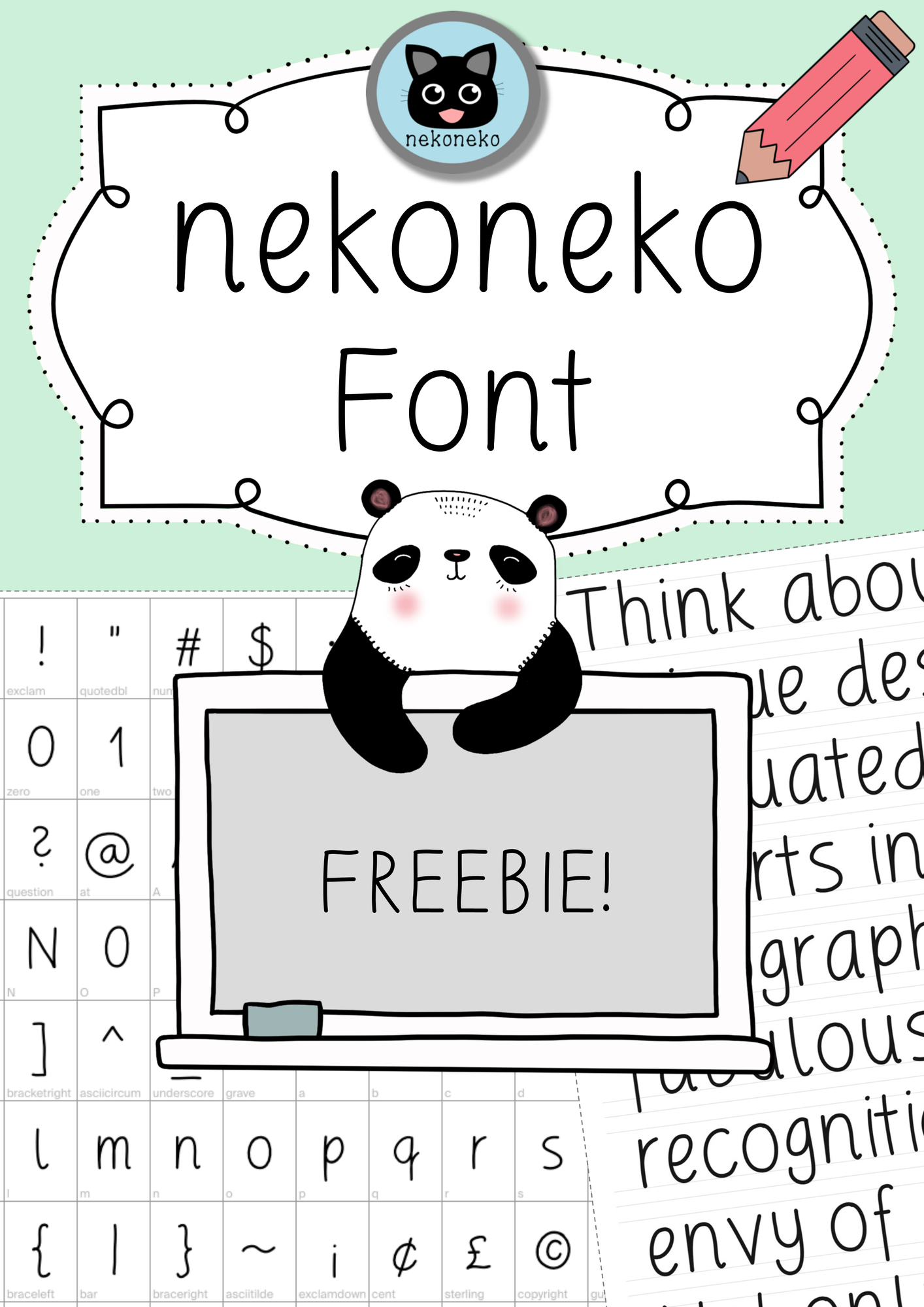
Immer wieder bekomme ich liebe Komplimente für meine Handschrift an der Wandtafel von meinen Instagram-Posts zum Wort der Woche. Darum habe ich nun meine Schrift digital aufbereitet, um sie euch gratis als Schriftart zur Verfügung zu stellen!
Sehr schön klar, aber dennoch ansprechend
Sehr gut lesbare Schriftart
Ich mag die Schriftart sehr und finds toll, dass sie kostenfrei zur Verfügung gestellt wurde.
Liebe diese Schriftart
So eine tolle Schriftart, die jede Raumdeko oder Arbeitsblätter verschönert! Vielen Dank!!!
Schöne Schrift
Diese Schrift ist wirklich ideal geeignet für die Gestaltung von Unterrichtsmaterialien
Lieblingsschrift!
Danke, dass du deine Schriftart kostenlos teilst! Ich liebe diese Schriftart, sie ist optisch ansprechend und gleichzeitig für die SuS gut zu lesen!
Ästhetische Schrift
Sehr ansprechende Schrift. Wäre es vielleicht möglich, die Buchstaben Øø, Åå, Ææ ebenfalls mit aufzunehmen? (Für uns Dänisch-Lehrer in Schleswig-Holstein) Das wäre wirklich super toll!
So eine tolle Schriftart!
Super Schriftart
Immer wenn ich diese Schriftart verwende, werde ich von Kolleg*innen darauf angesprochen, weil alle sehr begeistert sind. Habe sie selbst von einer Kollegin empfohlen bekommen und nutze sie sehr sehr gerne! Vielen Dank:)
Alle Buchstaben schulgerecht und gut erkennbar.